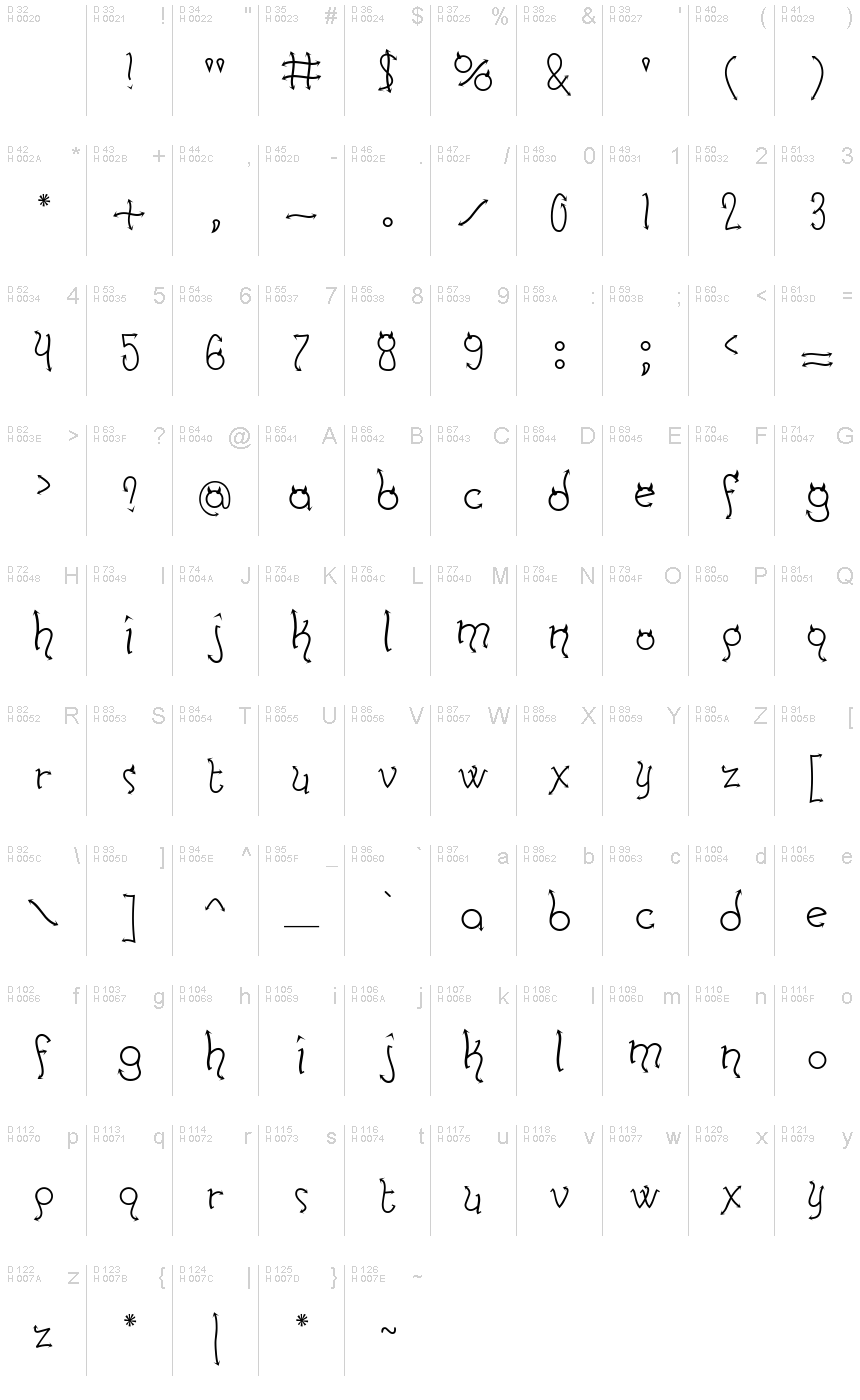
Horny Devils BV
Horny Devils BV di Blue Vinyl Fonts è un font gratuito in stile fumetto, spettrale e con un pizzico di umorismo nero. Ogni lettera si piega come una coda sinuosa, terminando in punte affilate che evocano un tratto graffiante e disegnato a mano, come se fosse stato scarabocchiato sul margine di un quaderno dell'orrore. Il tremolio dei tratti è dosato perfettamente per risultare dispettoso piuttosto che minaccioso, infondendo ai tuoi titoli un'energia ludica e sotterranea.
Horny Devils BV è ideale per locandine di Halloween, inviti a feste, insegne per case stregate, loghi di commedie horror, fanzine, titoli di giochi e grafiche per i social media. Il suo ritmo irregolare fa risaltare le frasi brevi e i titoli secchi, specialmente nei formati più grandi. Abbinalo a un carattere sans serif pulito e neutro per il testo principale, così le forme diaboliche rimarranno leggibili pur continuando a rubare la scena.